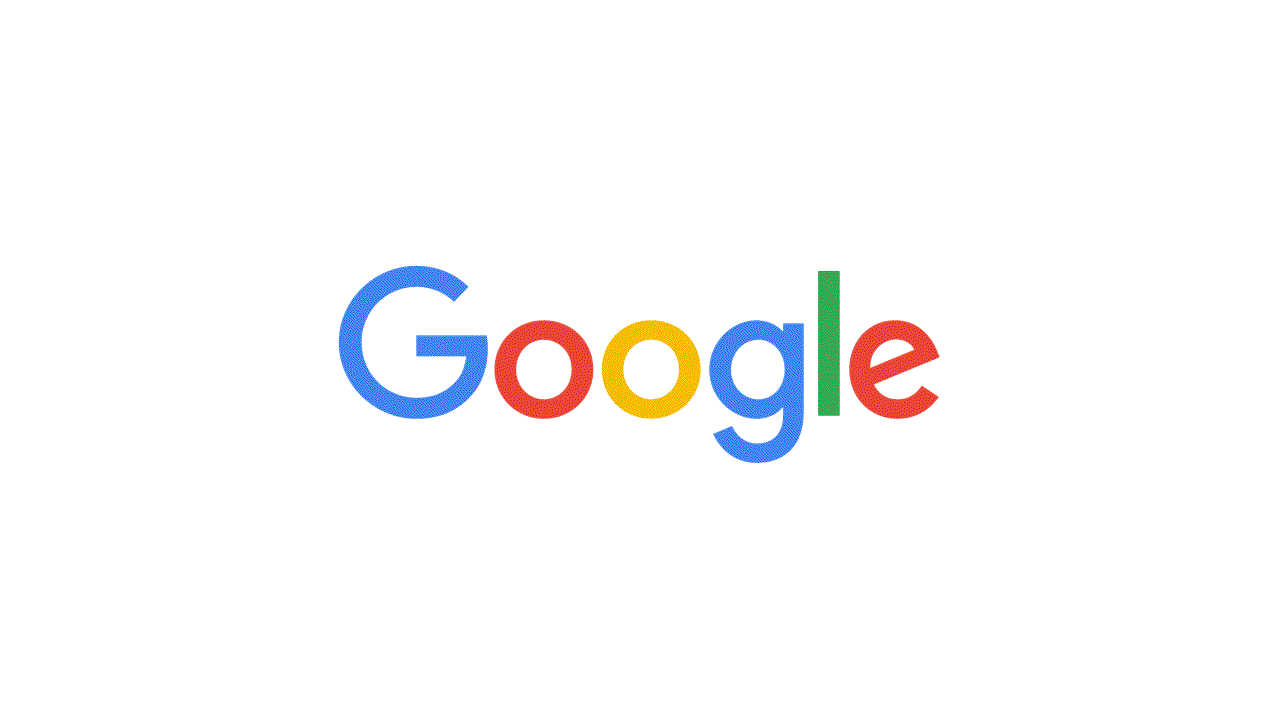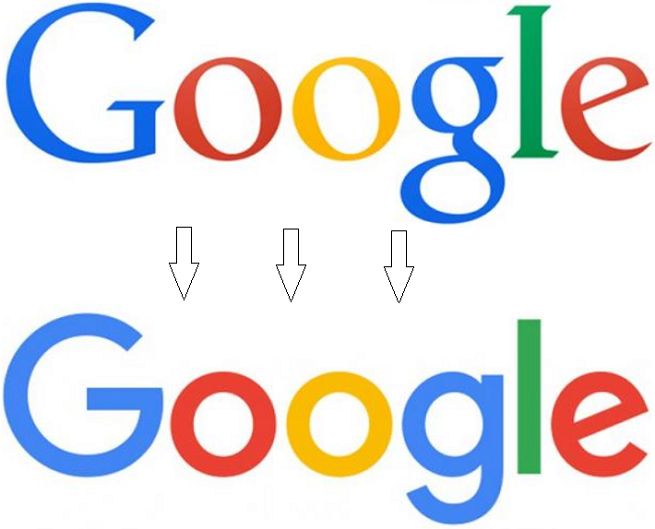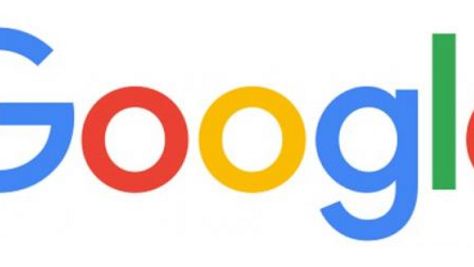
Koncern we wpisie na swoim blogu podkreśla, że przez ostatnich 17 lat bardzo zmienił się zarówno jego charakter, jak i portfolio oferowanych przez Google produktów. Początkowo Google kojarzony był wyłącznie z internetową wyszukiwarką, z której korzystano na komputerach klasy PC. Dzisiaj natomiast użytkownicy mają do dyspozycji wiele różnych produktów oferowanych przez koncern, i korzystają z nich na rozmaitych, w większości mobilnych, urządzeniach i platformach.
- Dzisiaj wprowadzamy nowy język wizualny, który oddaje tę rzeczywistość i wskazuje kiedy magia Google pracuje dla Was, nawet na najmniejszym ekranie. Jak widzicie, przenieśliśmy logo i filozofię marki Google ze świata strony w przeglądarce, do świata nieskończonej liczby urządzeń, których sercem jest komputer, i nowych różnorodnych sposobów wprowadzania informacji (np. dotyku, pisania czy rozmowy) - podkreśla Google w komunikacie.
Nowy znak graficzny Google zachował te same co poprzednio kolory, po 17 latach zniknęła natomiast czcionka szeryfowa, zastąpiona przez prostszy i bardziej przejrzysty krój pisma. Taki zabieg ma oddawać nowoczesny charakter firmy. Logo jest już prezentowane na głównej stronie wyszukiwarki Google w formie animacji pokazującej zastąpienie starego znaku graficznego przez nowy. Według zapowiedzi koncernu odświeżona identyfikacja marki będzie stopniowo pojawiać się w kolejnych produktach Google w nadchodzących tygodniach.